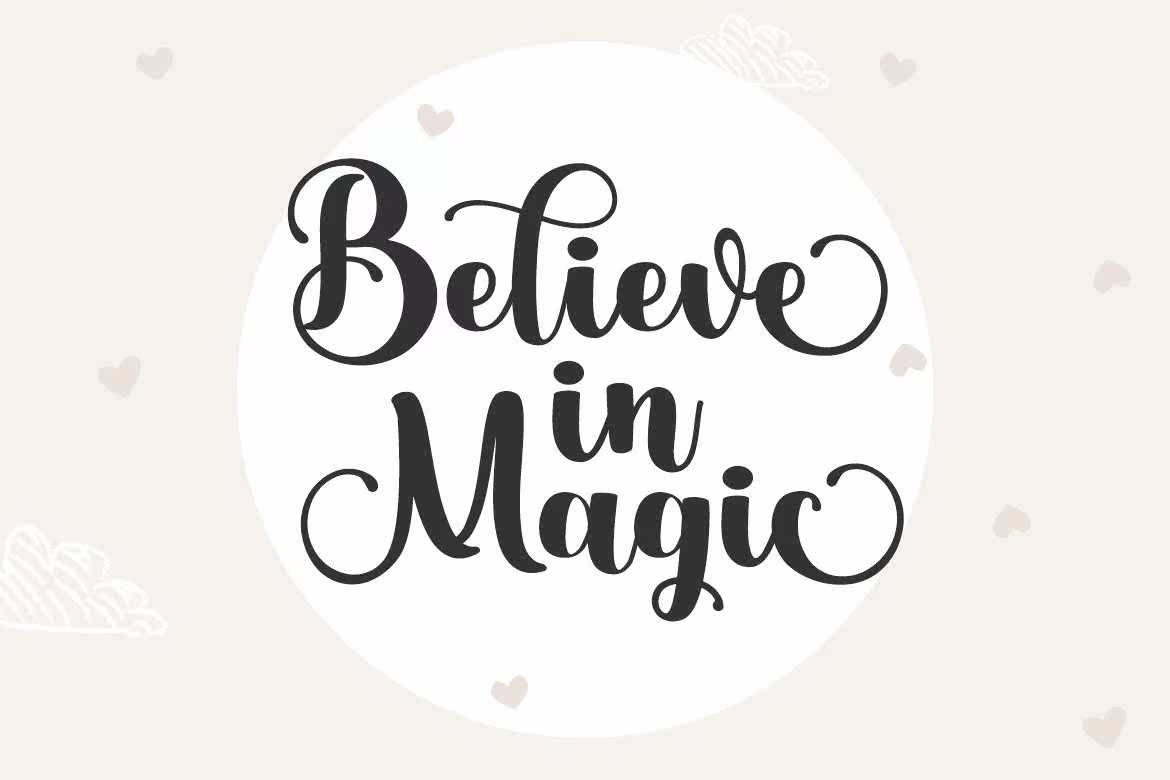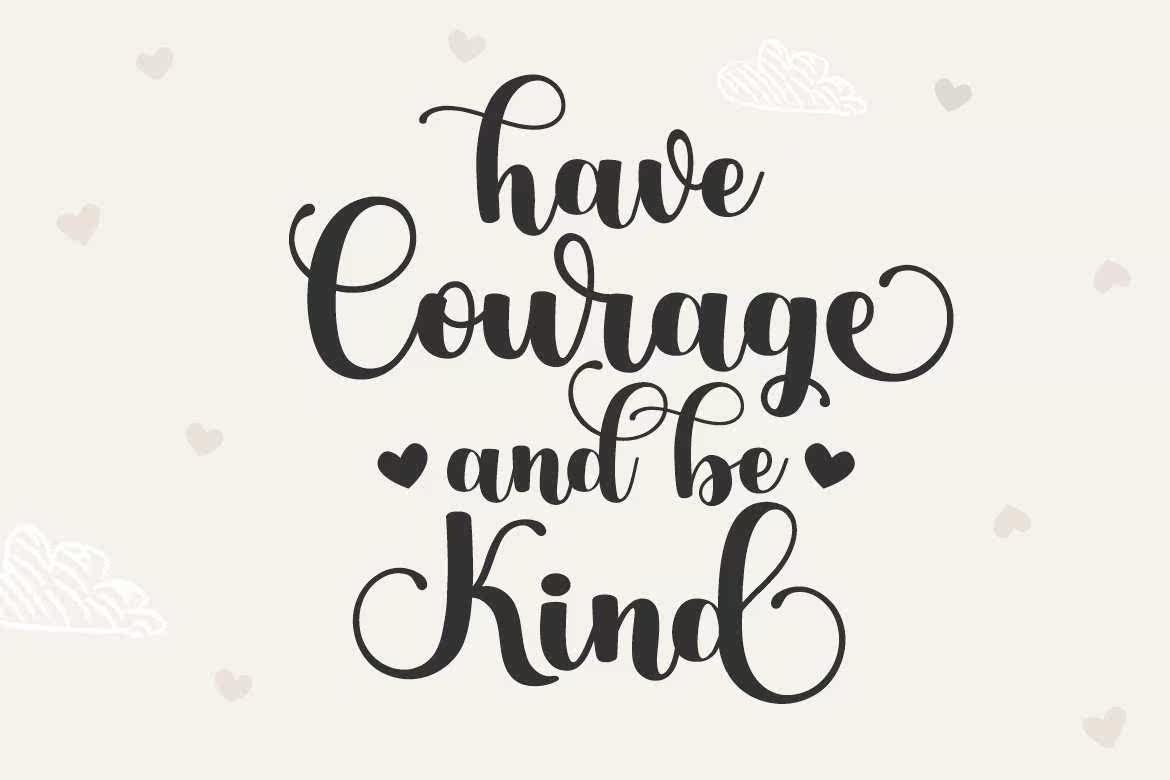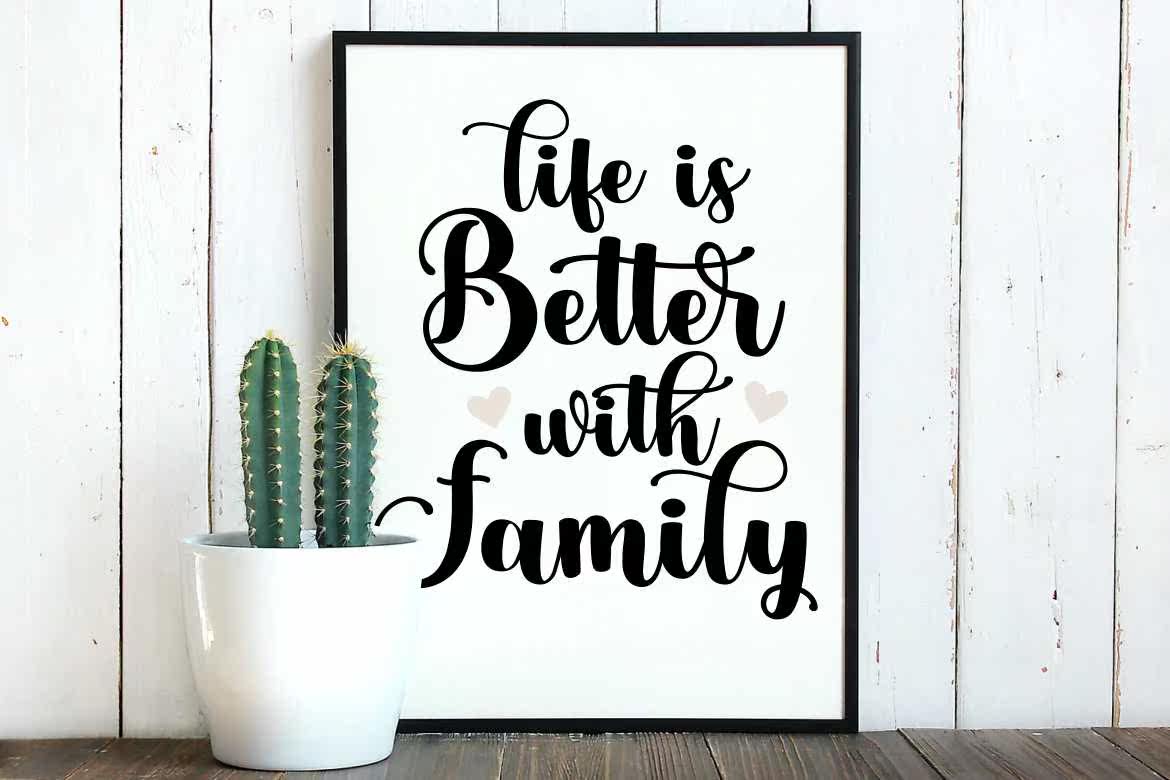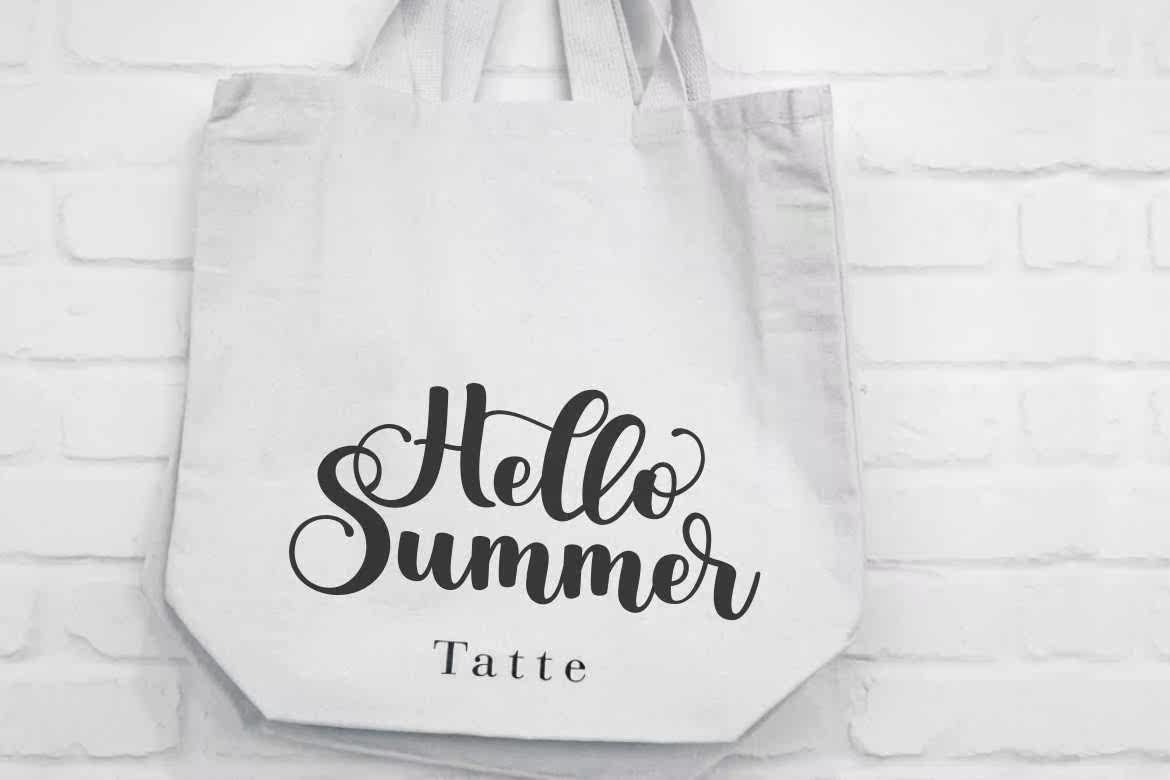
AsterikisaneLegant和BoldScriptFont,这两种字体的特点是相互关联的和精致的Swashes。这一原始字体将出现在从信头和标题到统计表的各种各样的字体中。该字体的编码意味着您可以访问字形和Swashese!AsterikisaneLegant和BoldScriptFont,这两种字体的特点是相互关联的和精致的Swashes。这一原始字体将出现在从信头和标题到统计表的各种各样的字体中。该字体的编码意味着您可以访问字形和Swashese!